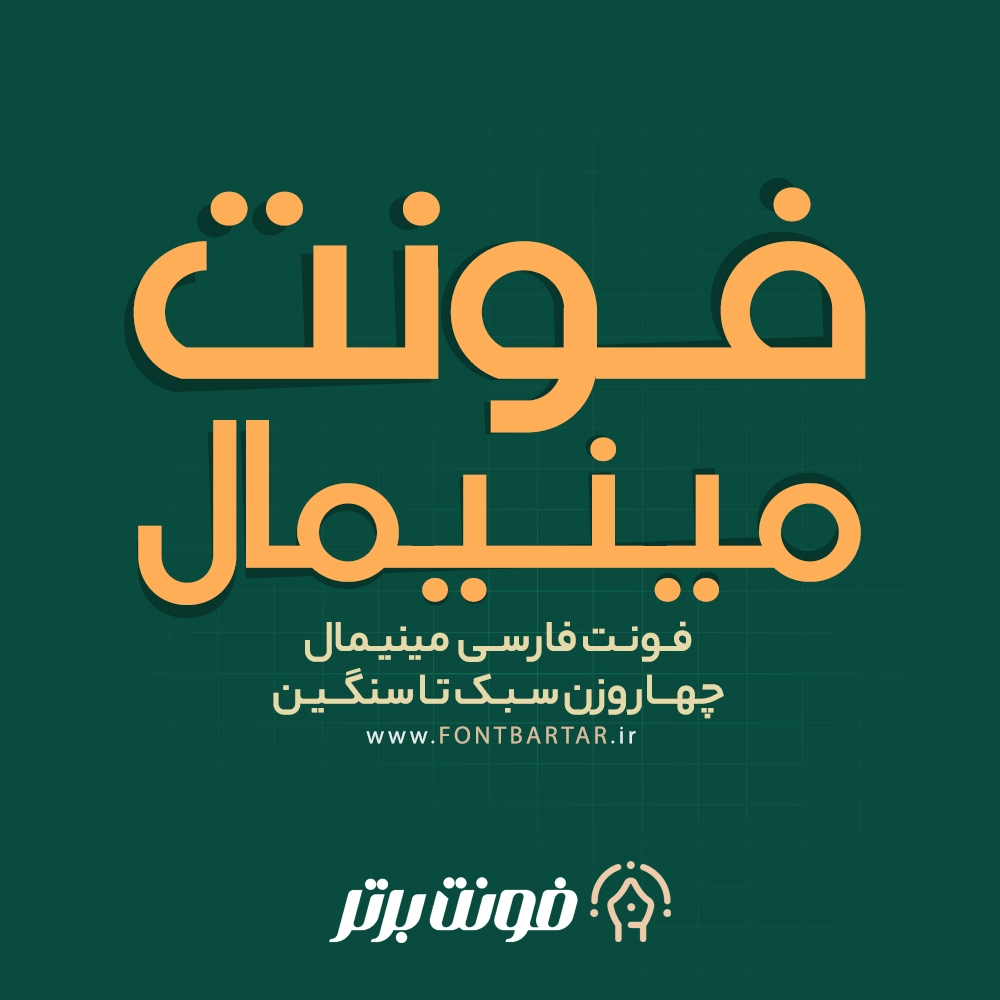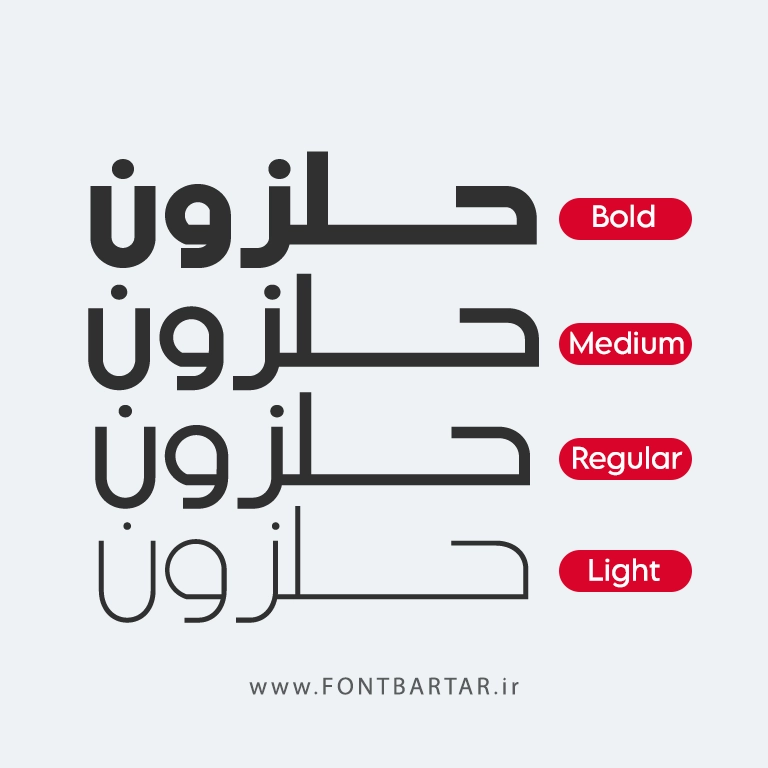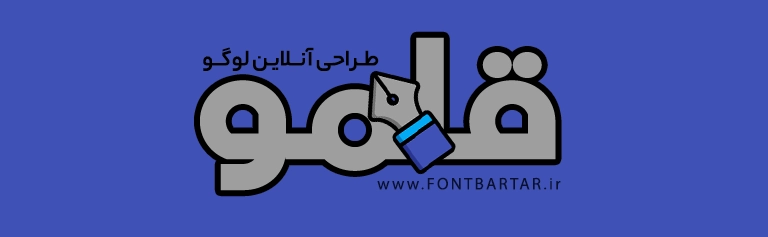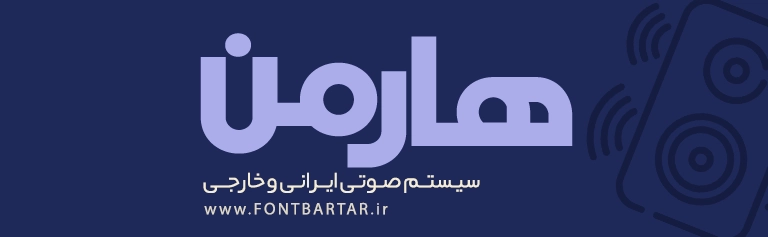
فونت مینیمال
Minimal font
دانلود فونت مینیمال | فونت ساده و مدرن برای طراحی حرفه‌ای
چرا فونت مینیمال فارسی؟
دانلود فونت مینیمال به دلیل سادگی، وضوح بالا و حس مدرنی که منتقل می‌کنند، انتخاب اول طراحان UI/UX و وب‌سایت هستند. این فونت‌ها در کنار زیبایی، سرعت بارگذاری بالایی هم دارند و باعث بهبود سئو سایت می‌شوند.
کجا میتونم از جدید مینیمال استفاده کنم؟
• طراحی استوری ،کاور پستهای شبکه های اجتماعی، پست های خبری ، آموزشی ،عاشقانه ، فانتزی ، کیوت و دپ
• طراحی جلد مجلات،پوسترها و تراکتها
• شعار و اعلان های تبلیغاتی
• عناوین وجملات تاکیدی
• متون طولانی
• عکسنوشته احساسی ، رمانتیک ، عاشقانه ، دپ و کیوت